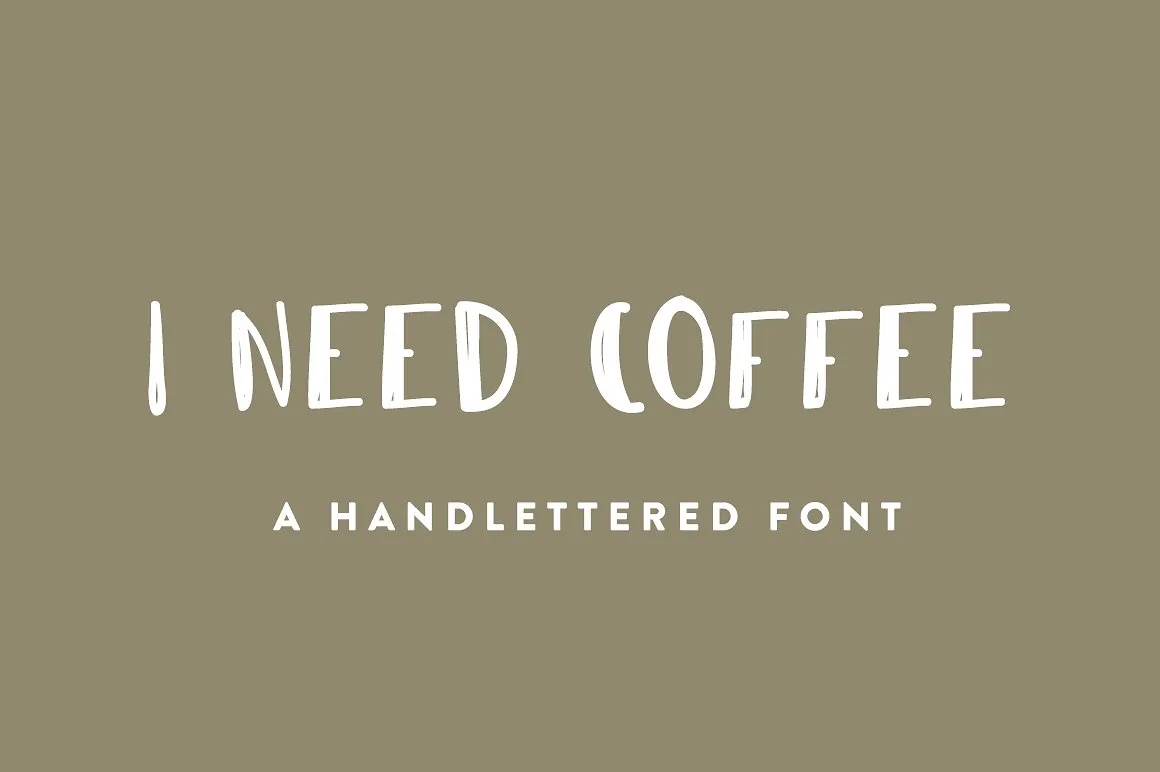
I Need Coffee Font – Download Grátis
Nós temos uma nova adição para a nossa coleção de fonts gratuitas! Introduzimos a I Need Coffee Font, um tira-gosto premium que você pode encontrar no Creativemarket. Desenhada pela The Fresh Exchange, essa fonte tem um toque casual e confiante, perfeita para criar gráficos para campanhas nas redes sociais ou imagens para seus blogueiros de moda. Com uma aparência bruta e criada à mão, ela transmite aventura e uma vibe descomplicada. Especialmente útil quando você precisa de um visual casual e autêntico em seu próximo projeto digital. A I Need Coffee Font é toda em maiúsculas, incluindo números e alguns símbolos de pontuação, tornando-a ideal para personalizar imagens de blog ou até mesmo gráficos promocionais. É o tipo de font que você pode usar sempre que desejar um visual casual sem comprometer a elegância ou profissionalismo do seu projeto. Em sua próxima campanha nas redes sociais ou em seu próximo post no blog, faça uma pausa e experimente I Need Coffee Font. Você não vai se arrepender de ter escolhido essa font exclusiva e versátil.